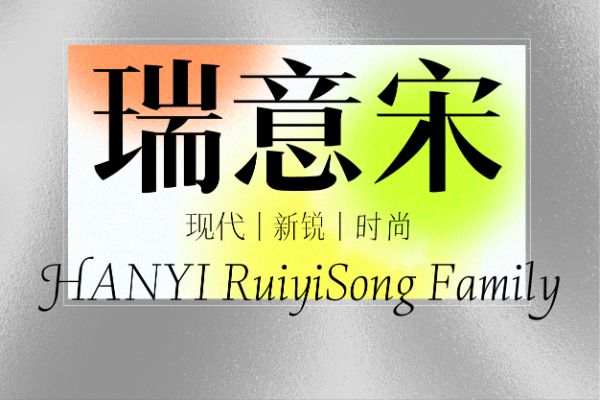
汉仪瑞意宋I 35W
汉仪瑞意宋W字体造型有着摩天大楼一般的高耸感、硬朗直线带来的速度感、线面强对比带来的凌厉感、微妙而有张力的曲线带来的力量感与精致感,同时又尽可能保留汉字书写的人文情怀,处处都表达着这个时代的审美取向。全新的汉仪瑞意宋W字体 ,分为长体、正体、斜体三个系列共22个字重。其中还包括四个小字号优化的字重。
战国栋
大连民族大学设计学院教师,SGDA协会会员,汉仪字库签约字体设计师